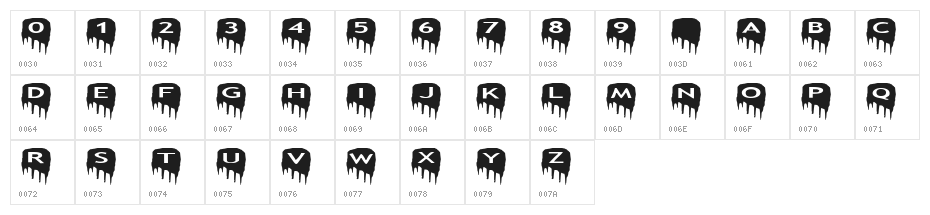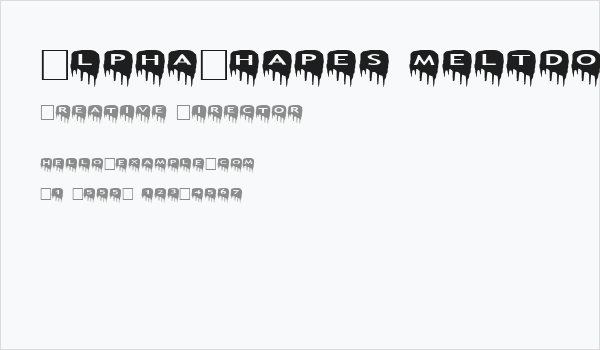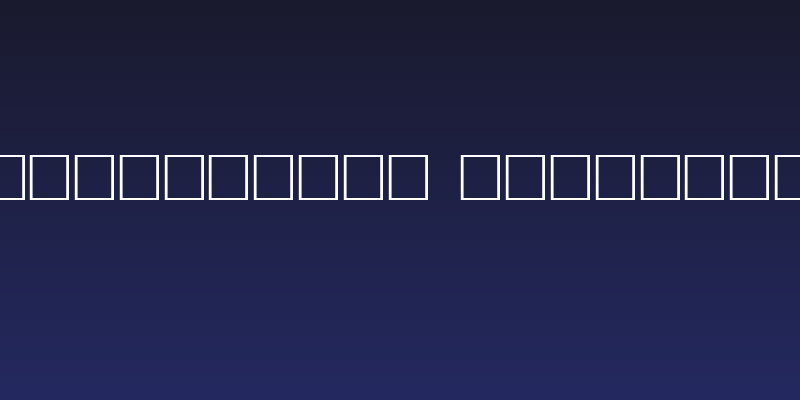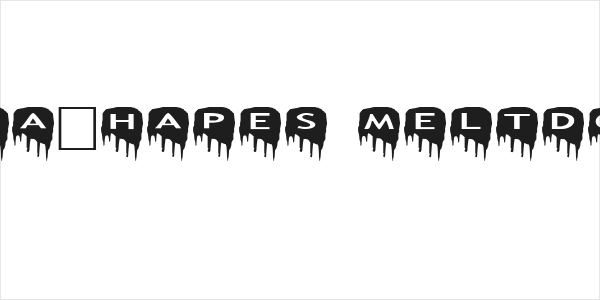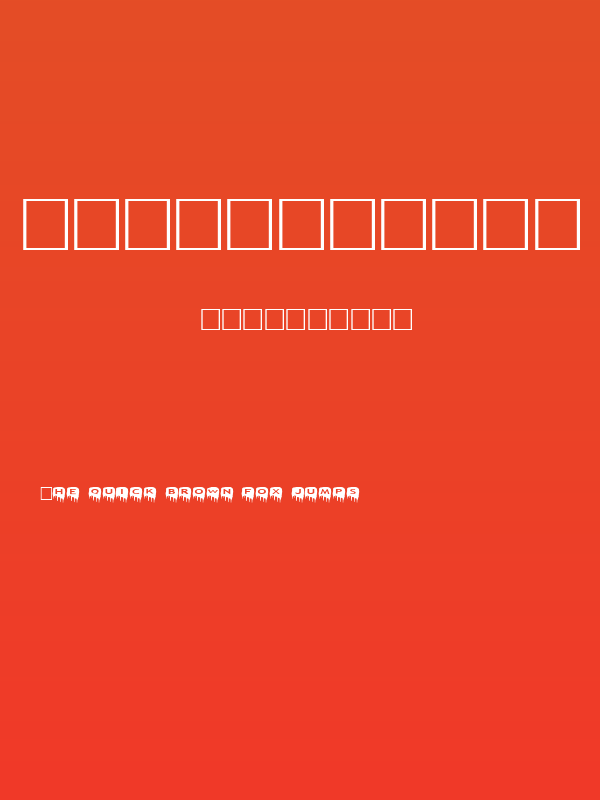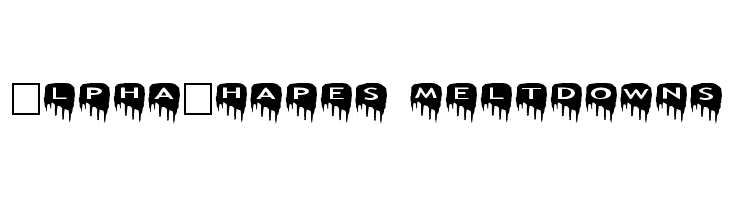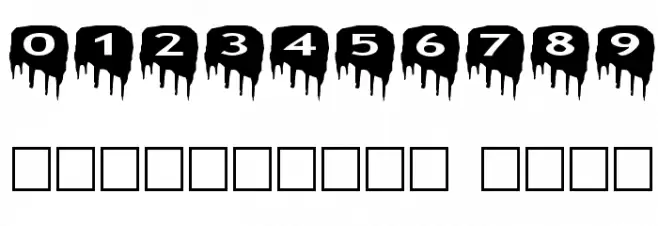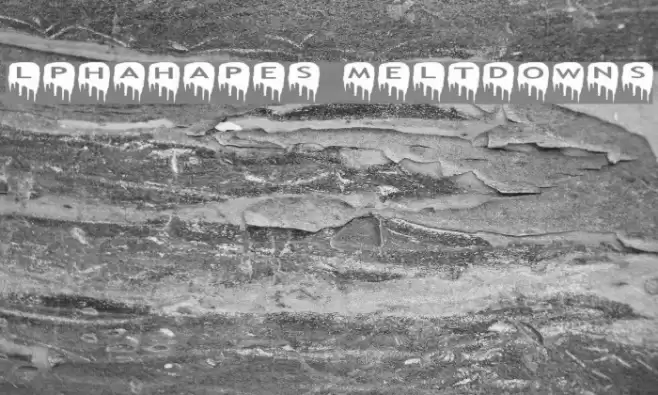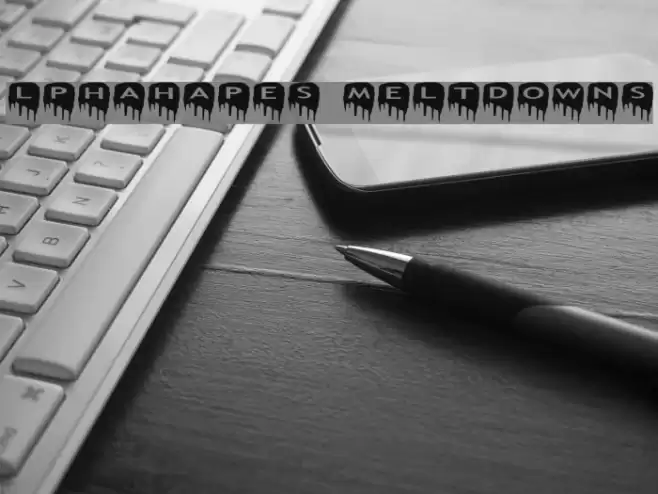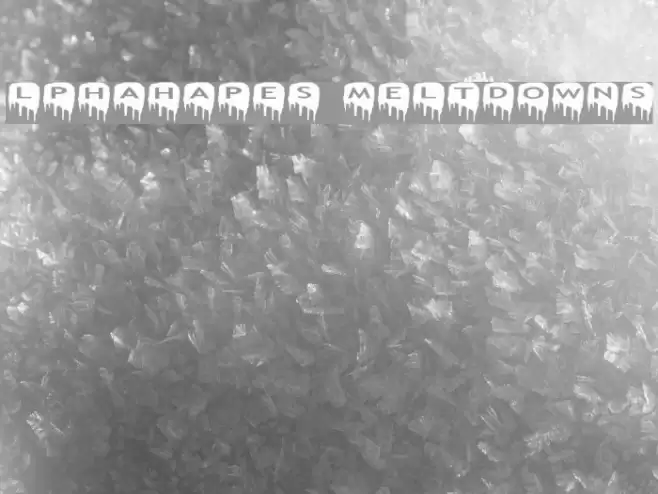
AlphaShapes meltdowns Font
| Proiecte propuse | Perfect for Halloween posters, horror movie titles, themed event invitations, and edgy graphic designs. |